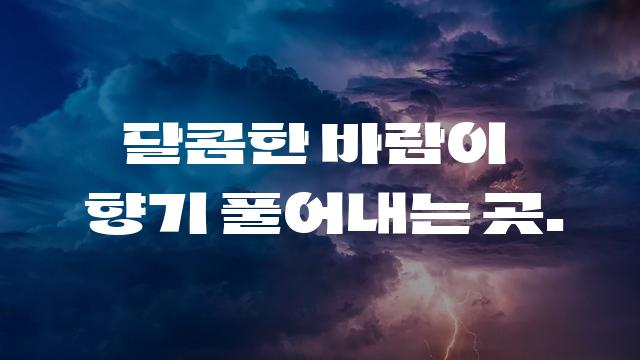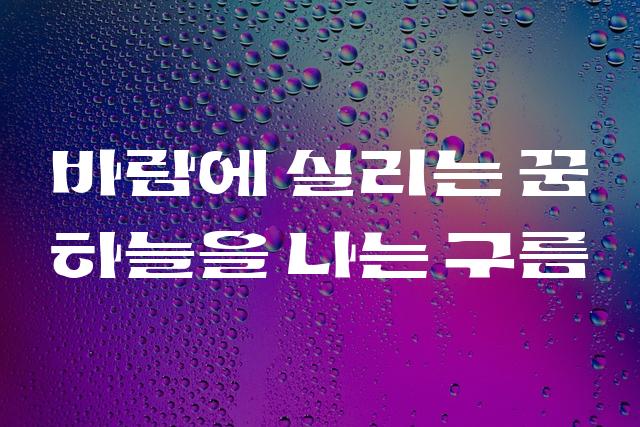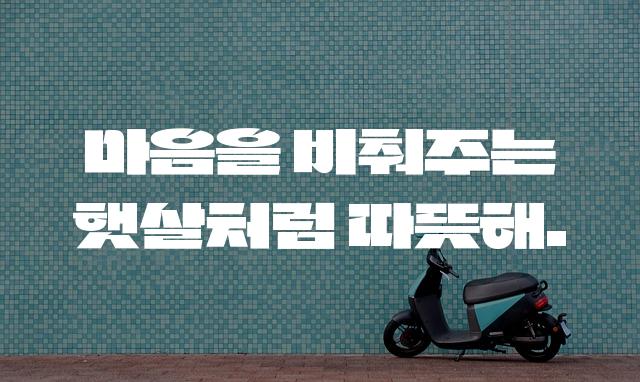
‘기후위기-한글-1979’는 제목용 장식 고딕 폰트로, 가로로 긴 형태와 두꺼운 스트로크가 특징입니다. 시각적으로 강렬하면서도 현대적인 느낌을 줍니다.
기후위기-한글-1979은(는)
기본 고딕, 두꺼운 스타일, 굵은 고딕, 장식 스타일, 단단함, 별모양/패턴, 길고/크고 계열의 생김새를 가지고 있으며
광고 캠페인, 디지털 광고, 소셜 미디어 등에서 자주 활용되며, 효과적인 메시지 전달에 적합합니다.
이 폰트는 광고/마케팅, 크리에이티브, 환경/에너지 분야에 잘 어울리며,
창의적인, 예술적인, 자연스러운 느낌을 담고 있는 것이 특징입니다.